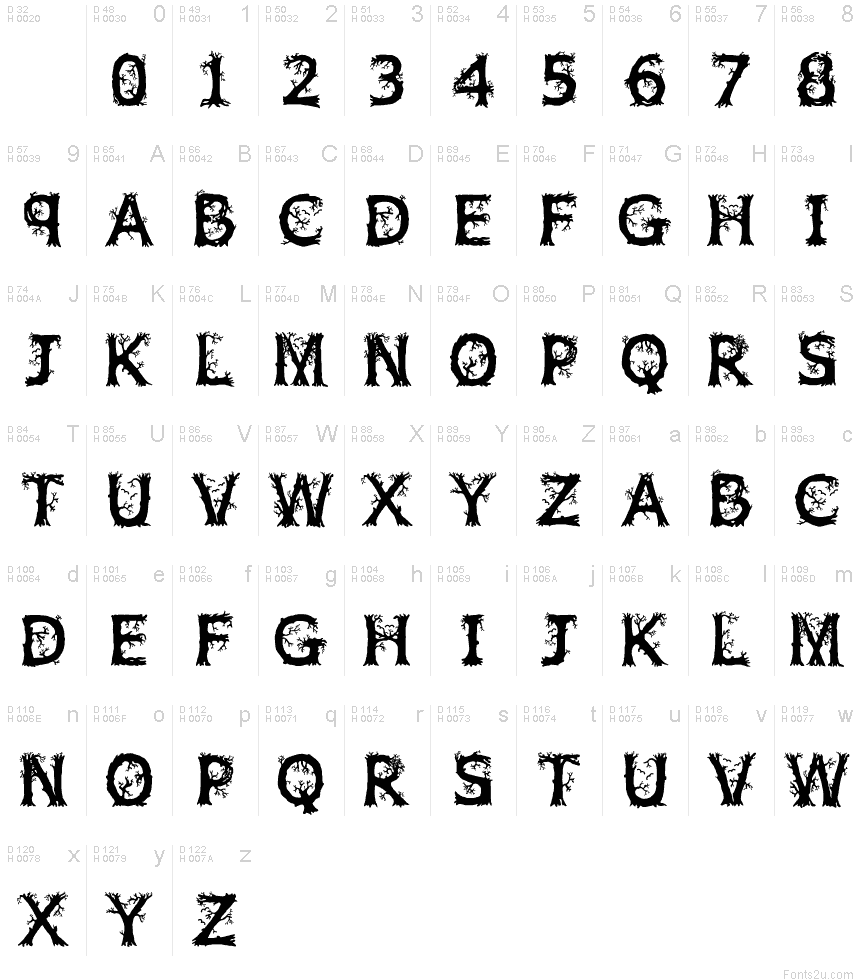
JF Wild Wood de Jester Font Studio es una tipografía decorativa y gratuita de estilo terrorífico, que parece esculpida directamente en árboles retorcidos y sin hojas. Cada letra está erizada de púas como ramas y bordes rugosos similares a la corteza, creando una textura de bosque oscuro, húmedo y viviente. Sus siluetas irregulares y sus formas negras y densas captan la atención al instante, haciendo que los títulos y palabras cortas parezcan advertencias clavadas en un árbol antiguo.
Con JF Wild Wood, puedes llevar tus carteles de terror, folletos de Halloween, señalización de casas encantadas, marcas de escape rooms, títulos de juegos y portadas de libros a un nivel de auténtica pesadilla. Esta fuente gratuita funciona mejor en tamaños grandes, donde sus detalles de ramitas pueden respirar; combínala con una sans serif limpia y neutra para el texto principal, para que este estilo salvaje y embrujado sea el verdadero protagonista.